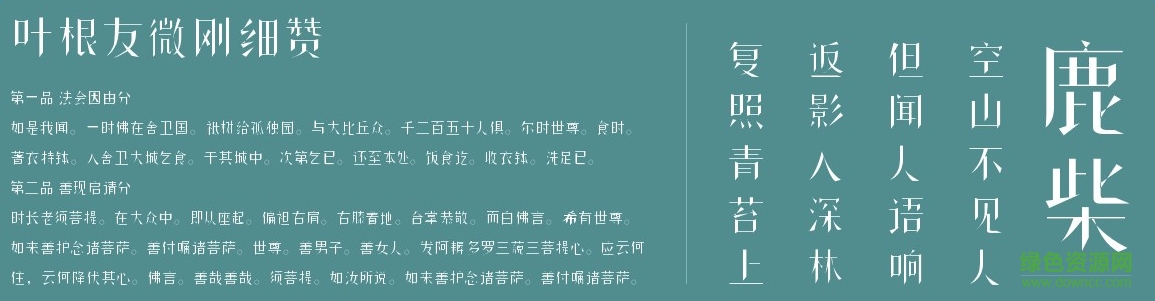
葉根友微剛細(xì)贊字體,2016年度最新發(fā)布的字體,該字體風(fēng)格獨(dú)特,簡(jiǎn)單大方而有銳氣,設(shè)計(jì)的理念來(lái)自竹林里砍竹子后的斜切面創(chuàng)意,利用這個(gè)創(chuàng)意應(yīng)用在書法字體上,形成了較好的體現(xiàn)效果。
葉根友微剛細(xì)贊字體,用途廣泛,是葉根友先生的印刷字體,字體非常纖細(xì),適用于文字排版等方面。各位字體收藏者可以來(lái)看看。